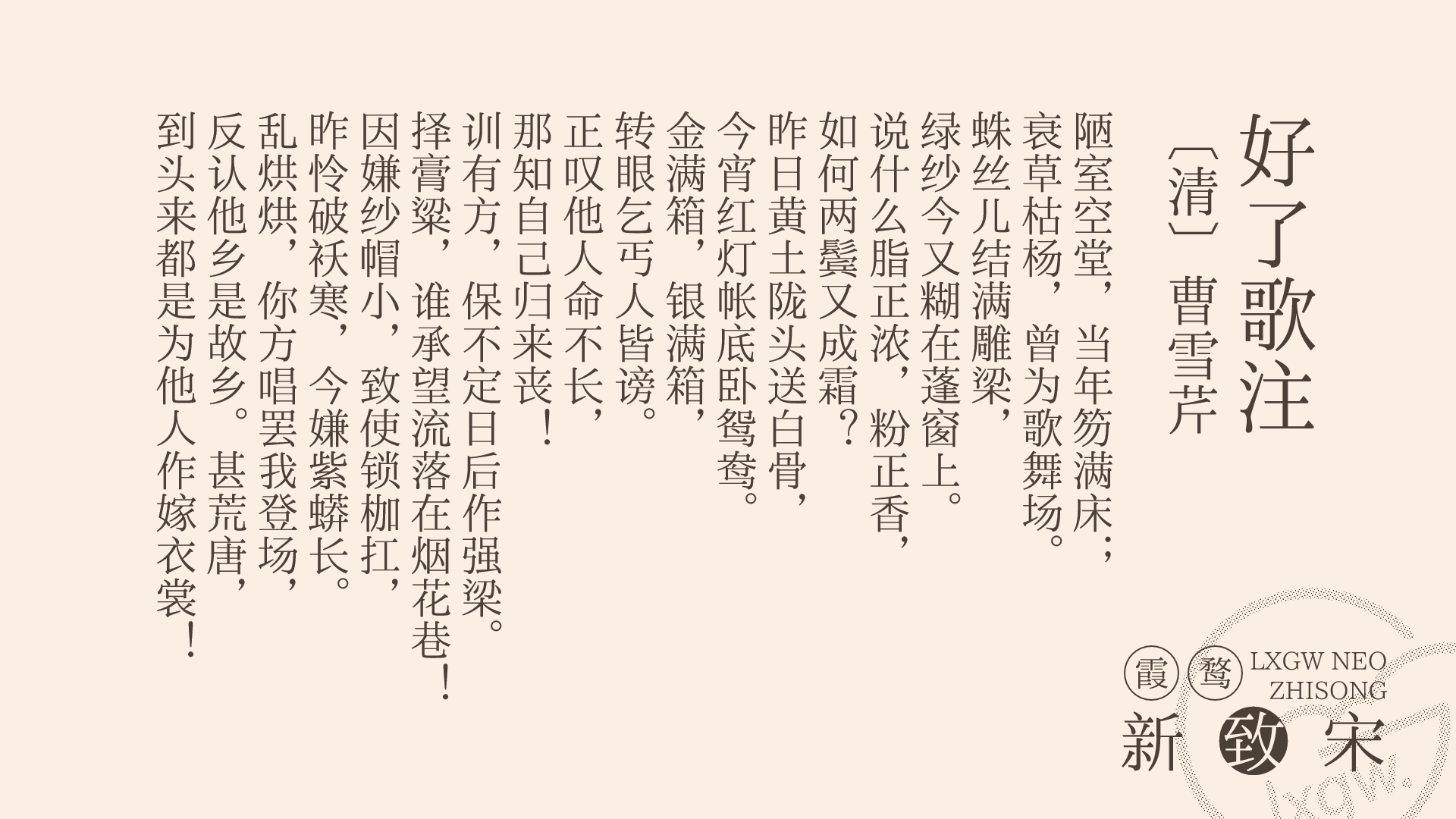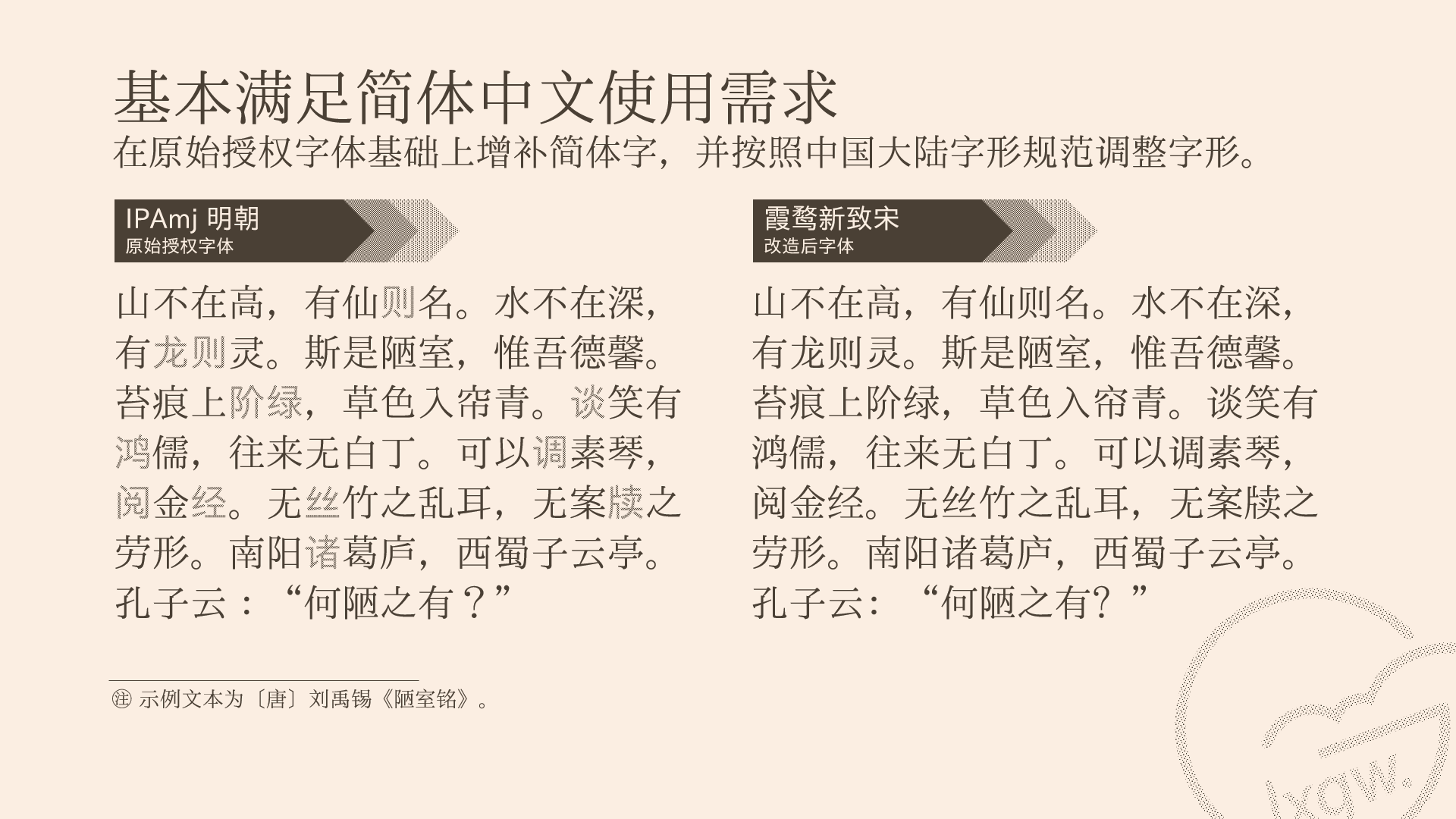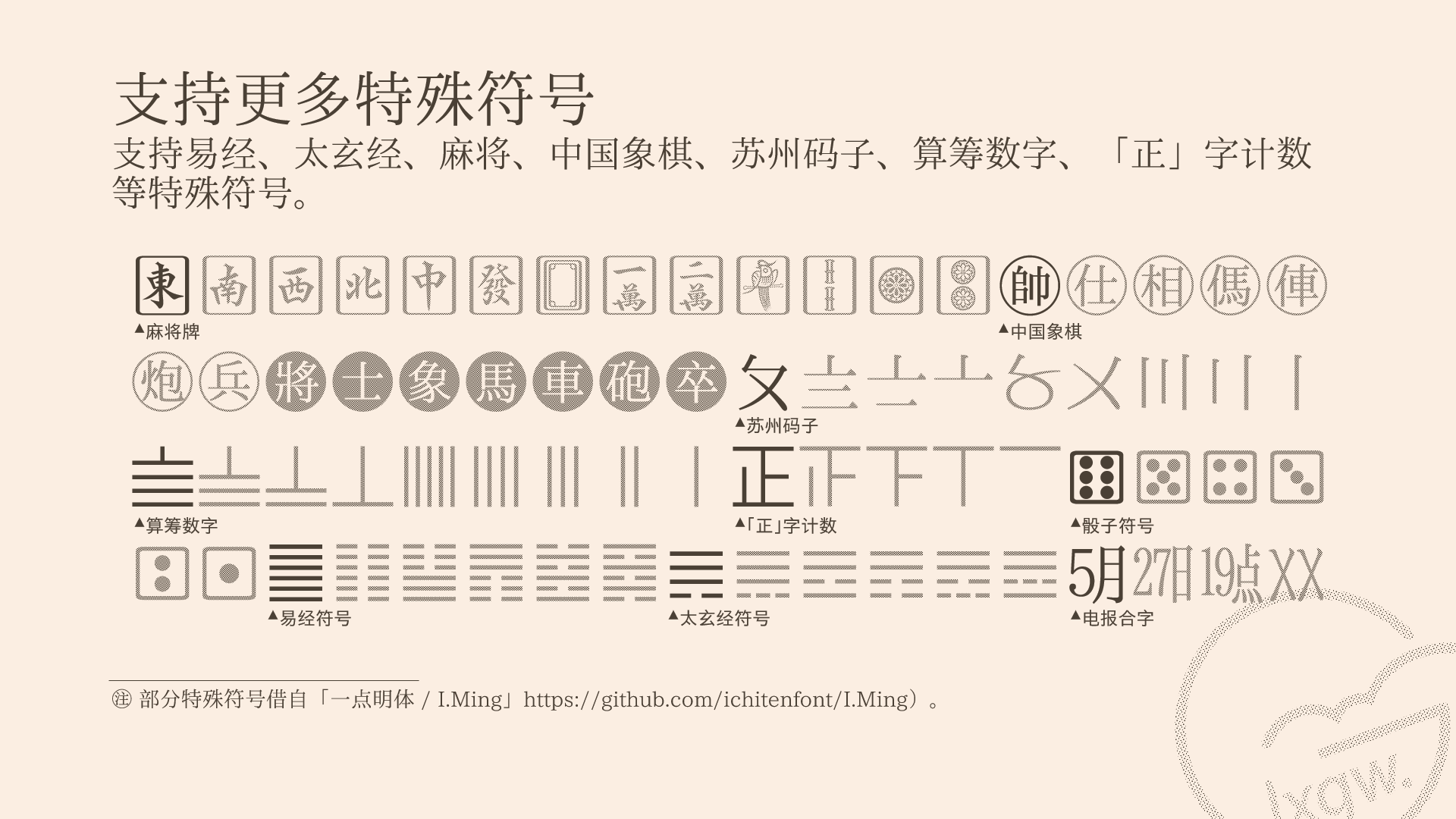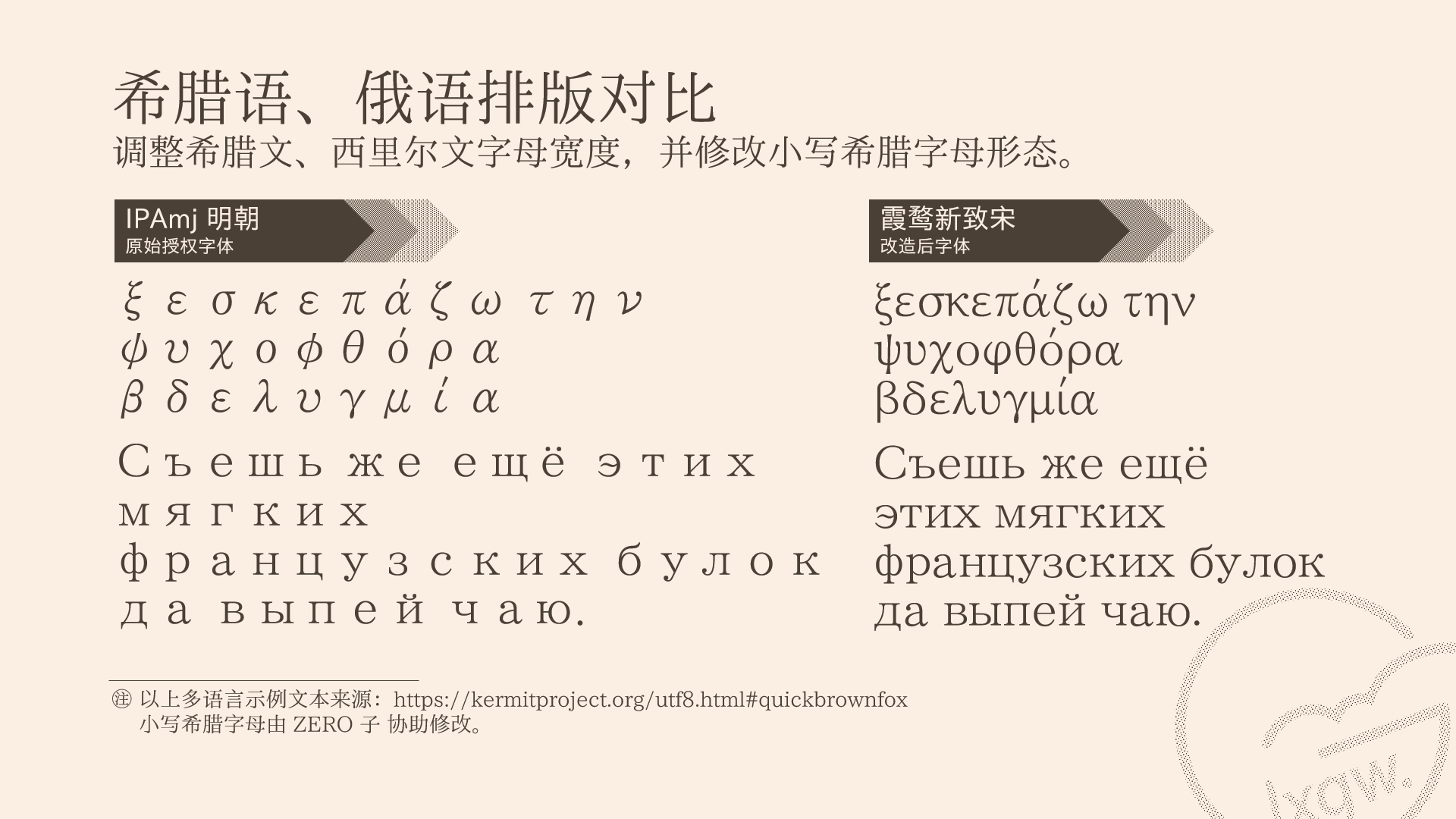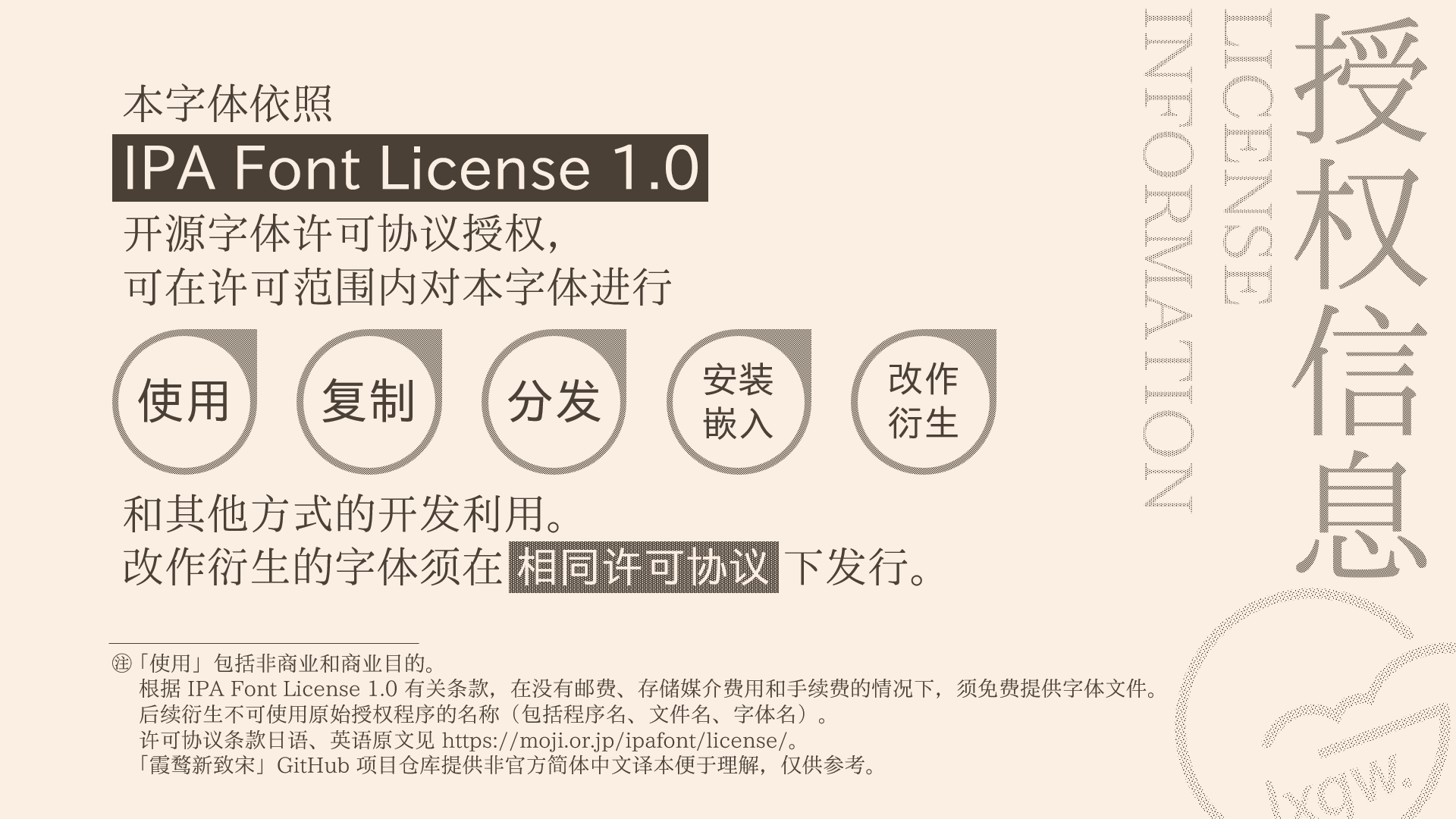
霞鹜新致宋(LXGW Neo ZhiSong)基于「IPAmj 明朝」,是将日本写法的字体改造成中国大陆规范写法的尝试,是一款衍生于日本「IPAmj 明朝」字体的免费商用中文宋体字型。
霞鹜新致宋(LXGW Neo ZhiSong)是「霞鹜新晰黑」(LXGW New Clear Gothic)的姊妹字体,该字体重做了希腊字母和西里尔字母,与原字体拉丁字母部分风格基本一致,更适合现代希腊文及西里尔文的排版;新增对越南语拉丁字的显示支持。
符号方面,支持易经八卦和六十四卦符号、太玄经八十一卦符号、麻将符号、中国象棋符号、算筹数字、「正」字计数等特殊符号。
免费商用宋体下载 |  霞鹜新致宋(LXGWNeoZhiSongCHS)字体样例
免费商用宋体下载 |  霞鹜新致宋(LXGWNeoZhiSongCHS)希腊符号样例免费商用宋体下载 |  霞鹜新致宋(LXGWNeoZhiSongCHS)特殊符号样例